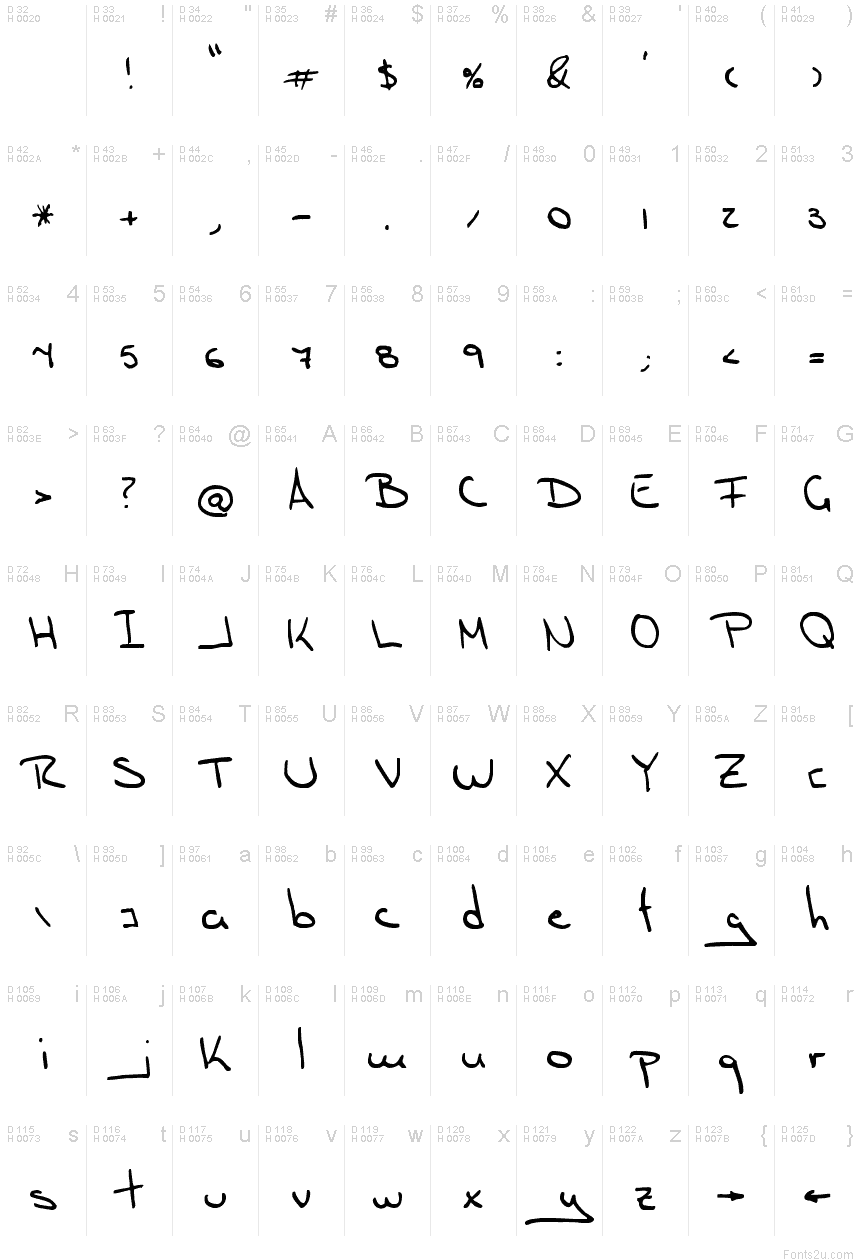
FG Augustin, volně dostupné ručně psané písmo od autorů Augustin Llerena a Font Garden, v sobě nese uvolněnou, lehce divadelní energii, jako by bylo načrtnuto fixou jedním rychlým tahem. Písmena kombinují vysoké, úzké tahy se zaoblenými křivkami a hravými háčky, takže linka působí improvizovaně a velmi lidsky nepravidelně.
Díky tomu se přirozeně hodí na nadpisy plakátů, menu do kaváren, obálky indie knih, přáníčka nebo obaly ve stylu scrapbooku, kde tento font svou osobností snadno unese i krátký text. Nejlépe vynikne v krátkých rolích, jako jsou titulky nebo jména, protože jeho rozmáchlé koncovky a ležérní rytmus potřebují dostatek prostoru, aby mohly zazářit.